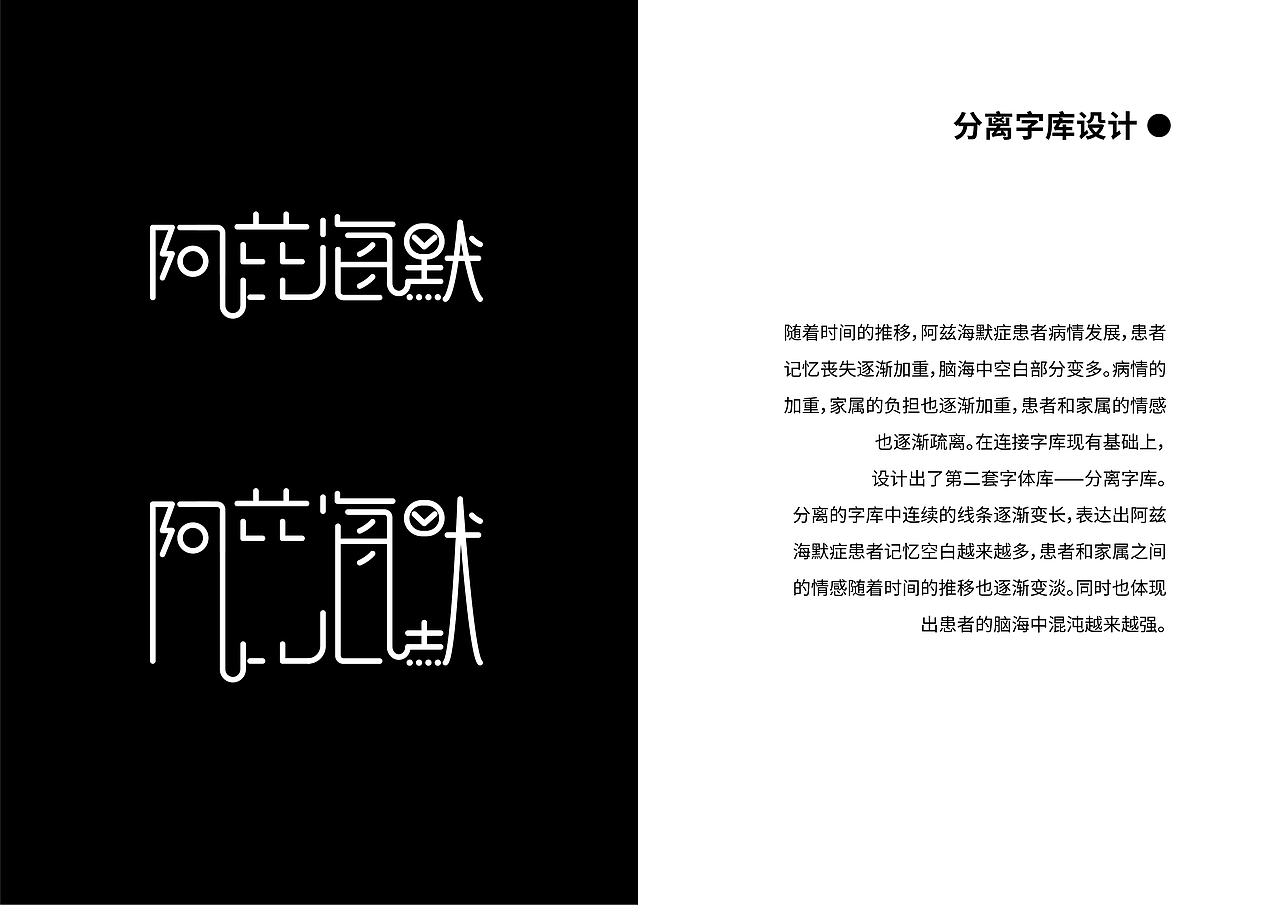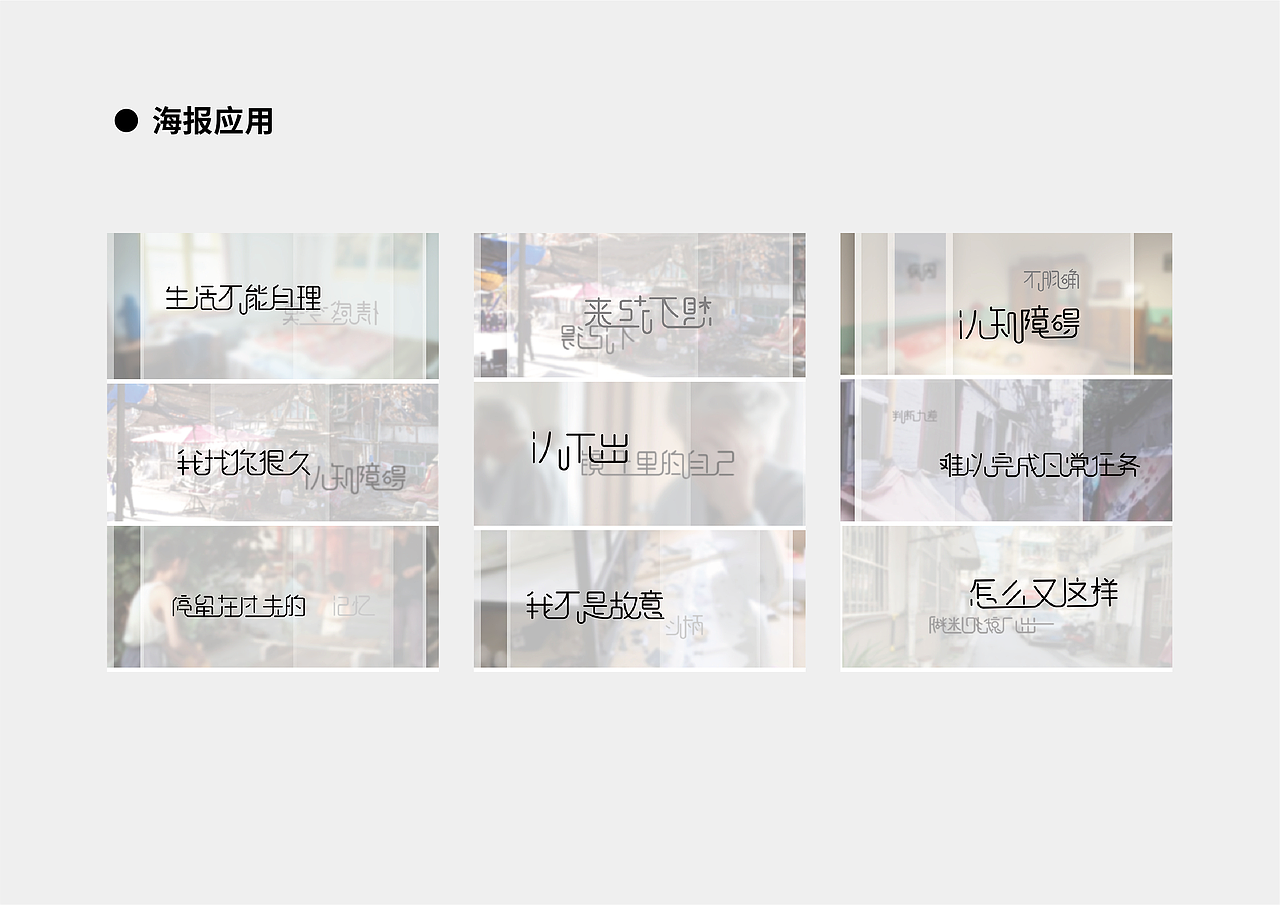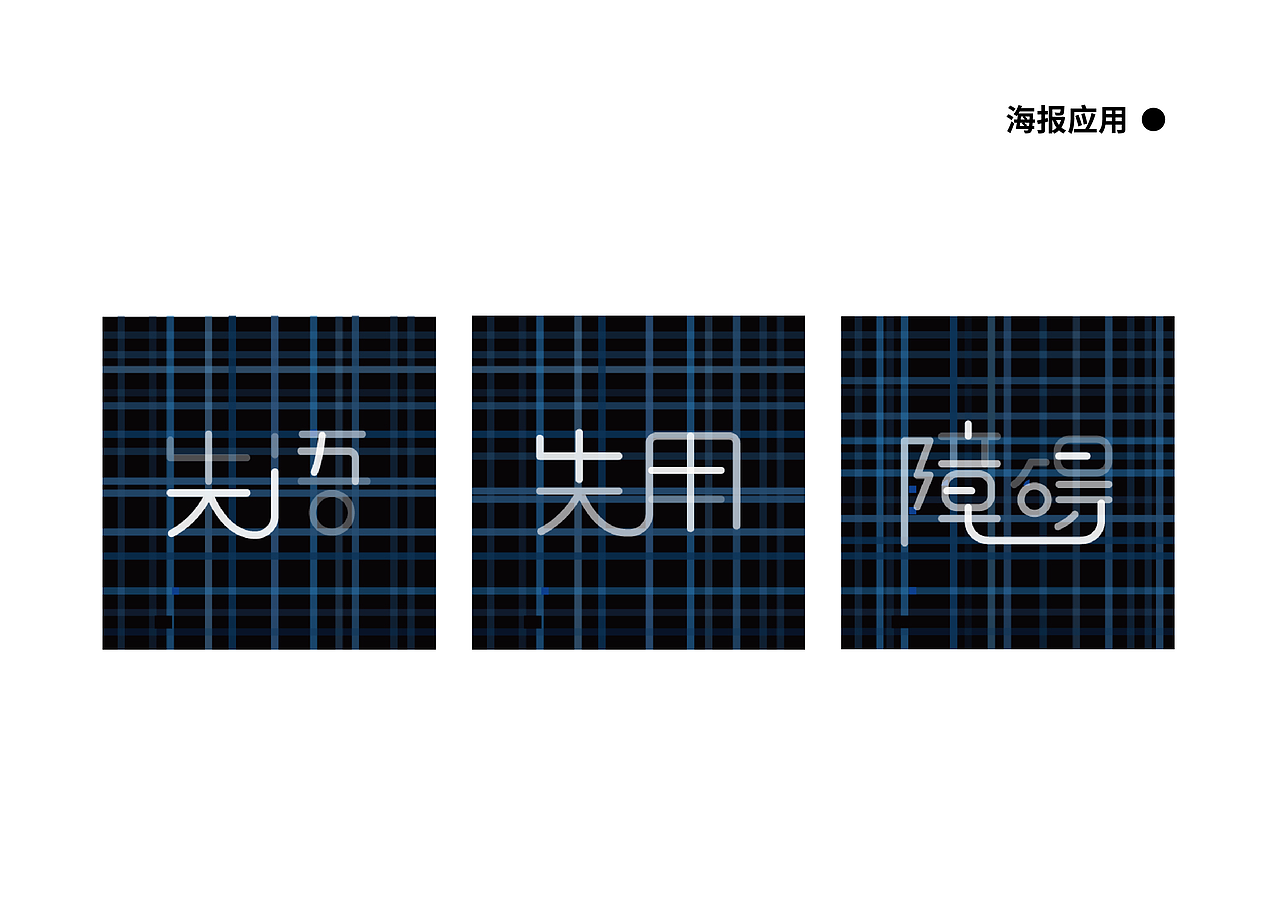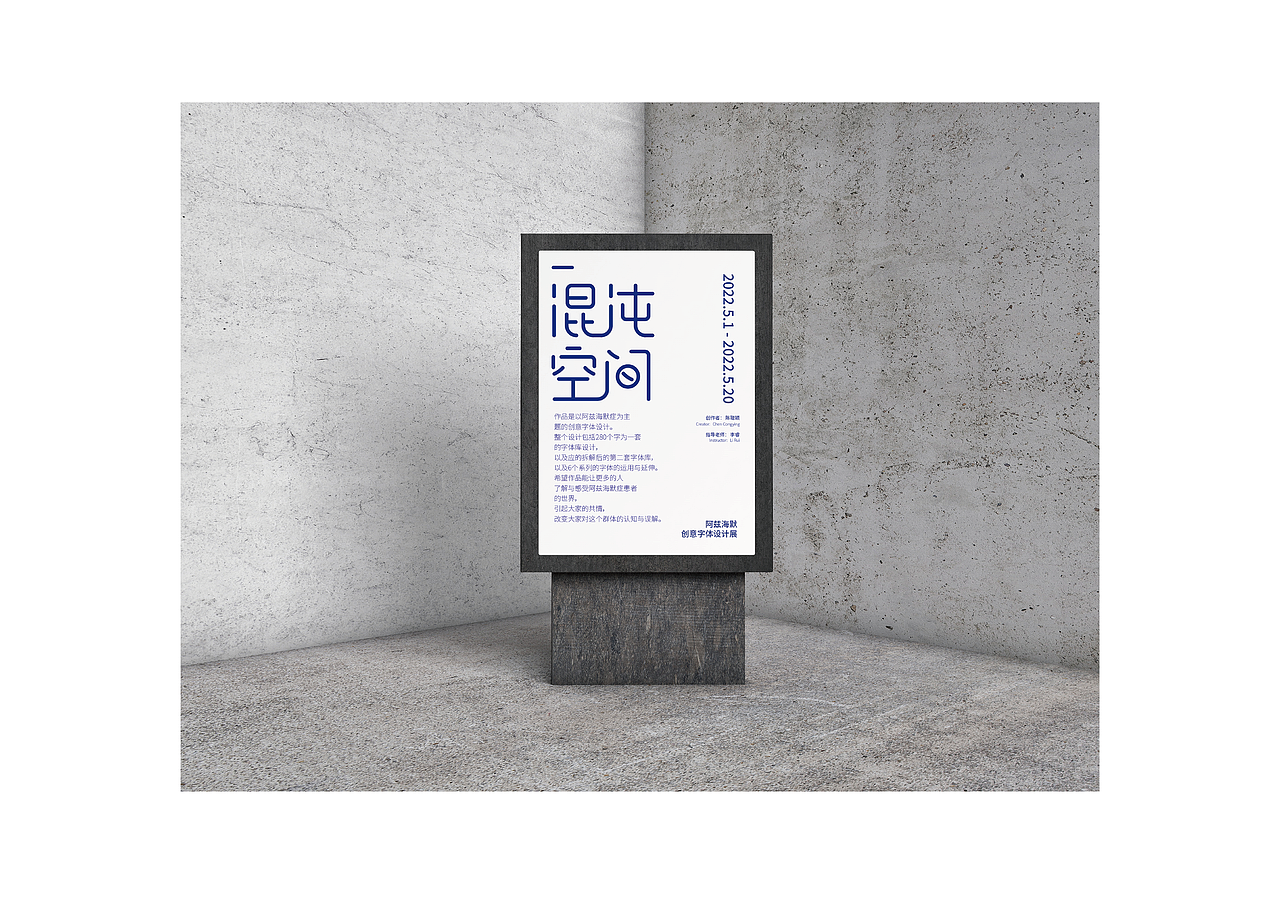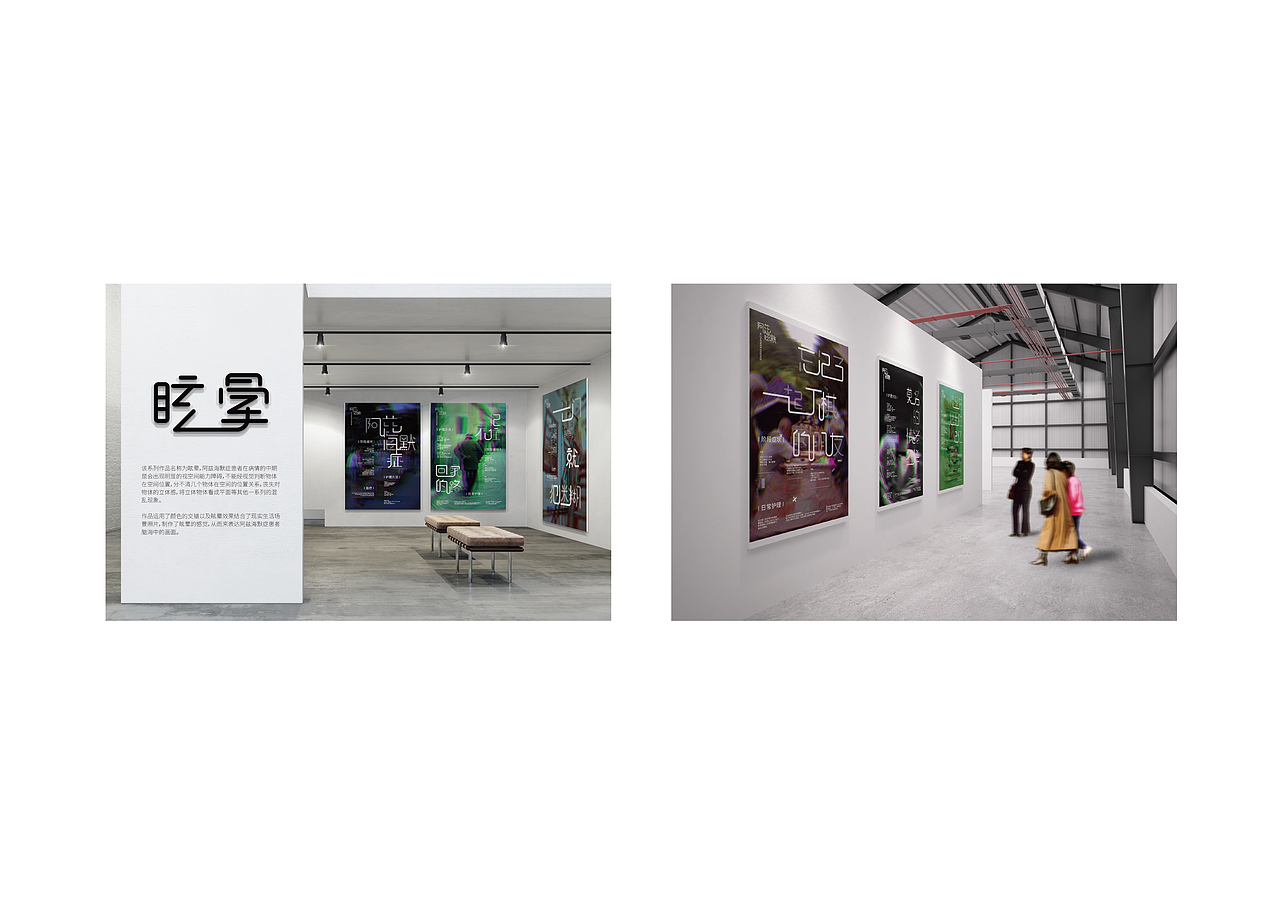
以阿兹海默为主题的创意字体设计
本设计课题是以阿尔兹海默症为主题,进行创意字体设计以及产品延伸。通过创意字体的表现形式,分析创意字体在社会中所起到的作用,以及创意字体作为信息和文化传播的载体如何呈现社会现象问题。本毕设用创意字体设计将观众带入阿兹海默症患者的第一视角,让观众对阿兹海默症建立科学认知,引发人们对此现象的思考和关注、让此类疾病的病患受收到社会更多的关注和帮助。
运用动画描绘从日常生活用品到字体的过程
动画设计